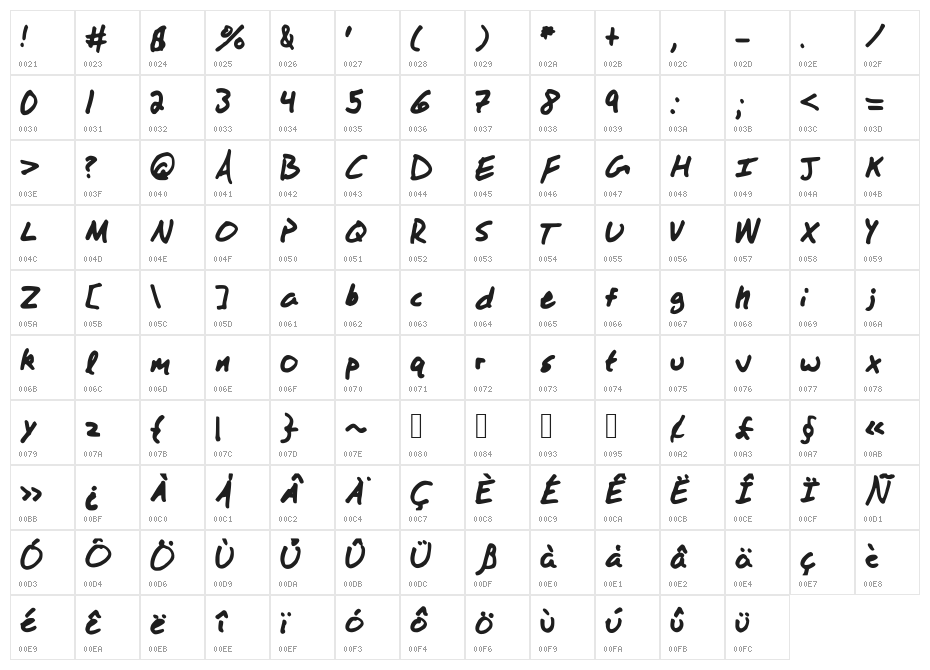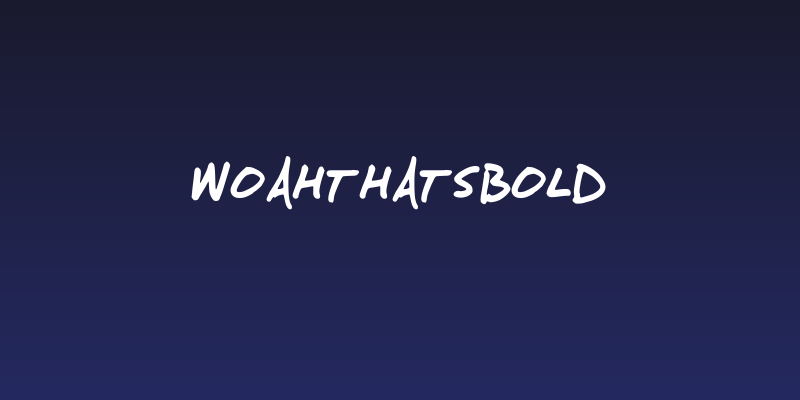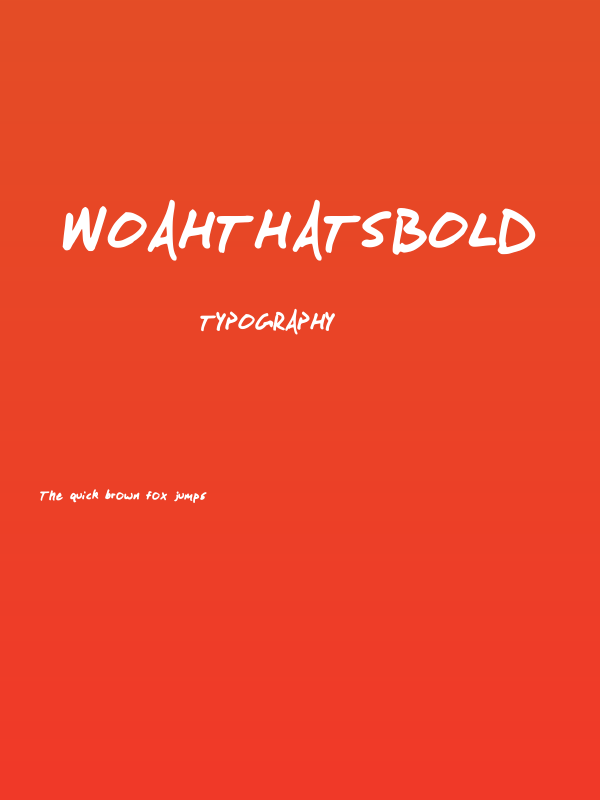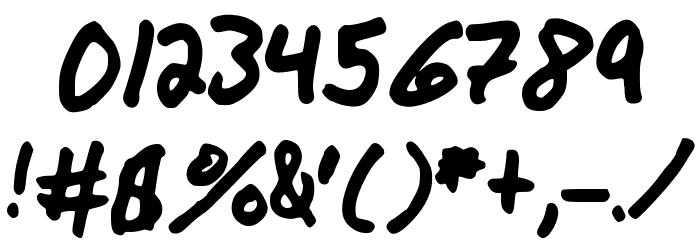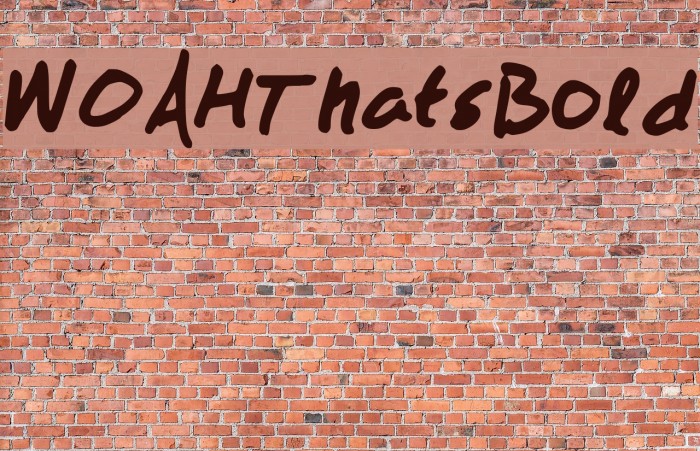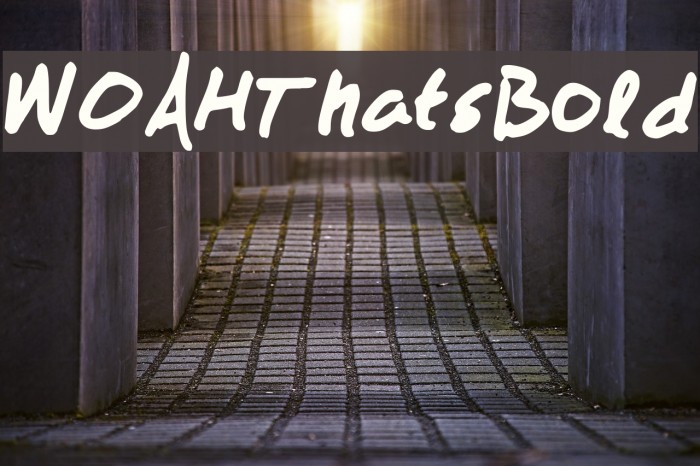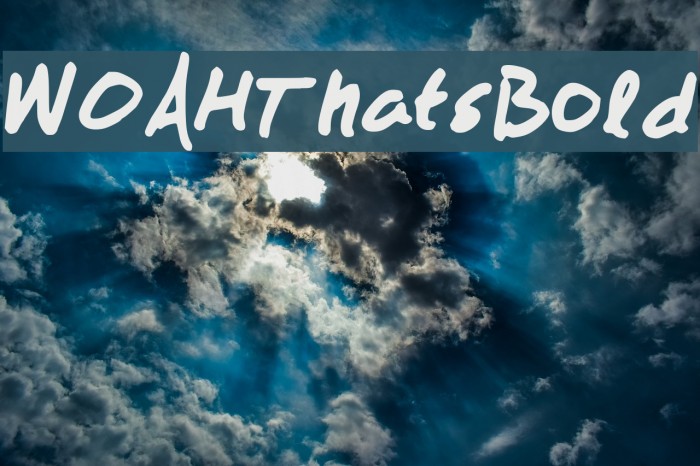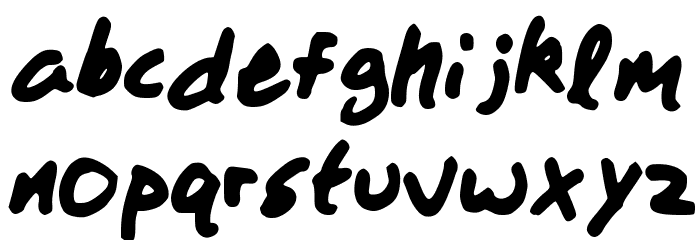
WOAHThatsBold Font
| Estilo general | Casual, Playful |
| Caso de uso | Headlines, Logos, Informal Text |
| Proyectos propuestos | Great for greeting cards, posters, social media graphics, and branding that requires a personal, informal touch. |